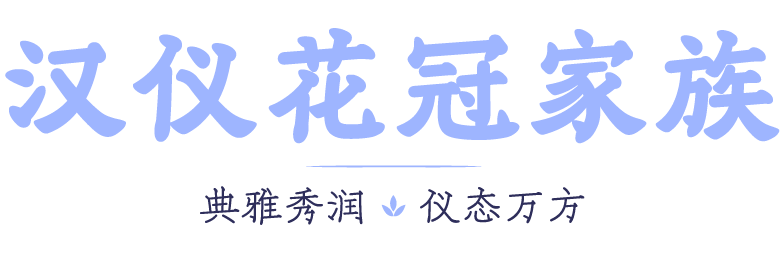
汉仪花冠字体介绍,汉仪花冠字体设计灵感
汉仪花冠家族是由汉仪字库签约设计师秦嘉霖合作设计的一套带有风格变化的家族字体。该字体家族从古籍刻本和植物花卉中提取灵感,字形中宫紧凑、撇捺舒展,仪容雅俊、典雅秀润,如绽放的鲜花般芬芳馥郁。故而该字体家族适合用在美妆珠宝、服饰衣帽、糕点茶饮、文创周边等各种需要表现中式、秀丽、典雅风格的场合。
该字体荣获 Hiii Typography 2018 中英文字体设计大赛专业组/中文排版字体入围奖。
汉仪花冠家族是一套足以打破家族字体概念的字体。传统的中文字体家族,一般仅会做笔画粗细和字面比例的变化。而该字体家族充分发挥了线性插值技术的潜力,实现了硬笔风格和软笔风格之间的平滑过渡,创造出这套既带有粗度变化又带有风格变化的家族字体。
该字体家族共包含 55/65/75/85 四款字重。细体如早春嫩枝般柔韧硬朗,粗体如花瓣一样软嫩舒展。这样的变化极大地拓宽字体的适用场景,从大标题到正文都有适合的字重可以选用,便于设计师将该套字体应用在各类视觉层级的场合。
汉仪花冠家族的创作灵感,源自明末汲古阁精钞本《离骚草木疏》。该钞本通篇用精美的小楷抄写,文字娟秀鲜丽、婉转玲珑、清新易读,属明末钞本中的佳品。
设计师在参考该钞本时并没有遵循复刻字体的常规套路,而是从钞本中提取、归纳字体的结构特征,并在此基础上做创意设计。设计师放大了原字形结构向外舒展的态势,强化了结构的扇形特征,使其能展现出鲜花怒放一样的形态,因此得名“花冠”。
汉仪花冠家族的细体(55 字重)是一款硬笔等线体。这款字造型简洁,有着早春嫩枝般柔婉有韧性的线条,笔画弧度细腻而有弹性,为整个字形增添生命力。
这款字体笔画设计融合了几种常见字体的笔画风格:横向笔画倾角一致体现出仿宋体的特征;顿笔和饰线展现出宋体字的风貌;撇、捺、勾、提等笔画的细节处理,则透露出一些楷体书写的笔意。
汉仪花冠家族的粗体(85 字重)是一款有着粗细变化的软笔字体。该字体的笔画有明显的楷化痕迹,从等线字体变成了带有运笔粗细变化痕迹的字体。粗体的笔画造型比细体拥有更多细节,如同绽放的鲜花一样,浓艳醇厚,芬芳馥郁。
汉仪花冠家族的西文部分,由汉仪字库西文设计师刘嫣然设计。设计师参照中文的设计思路,完美还原了字体家族由细到粗,由硬笔到软笔的变化过程。大写字母参考西文古典比例,带来典雅复古之美。小写字母适当地拉高了 x 字高,便于中西文匹配和谐。